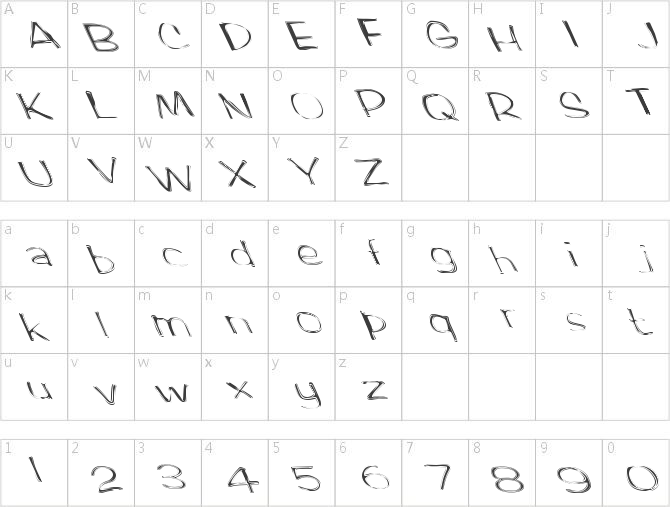
FZ HAND 2 CONTOUR LEFTY
FZ HAND 2 CONTOUR LEFTY介紹
FZ HAND 2 CONTOUR LEFTY字體字庫是一款讓人賞心悅目、百看不厭的英文字體,適合各類廣告和產(chǎn)品包裝設(shè)計應用,字體大小0.08MB,格式為ttf字體,上傳用戶是瀨子,作者/版權(quán)方為未知